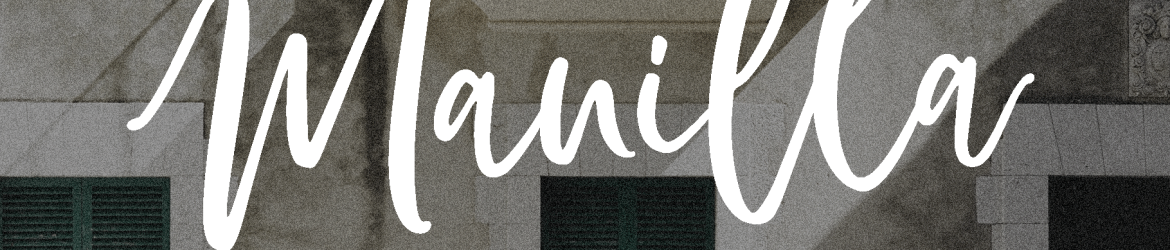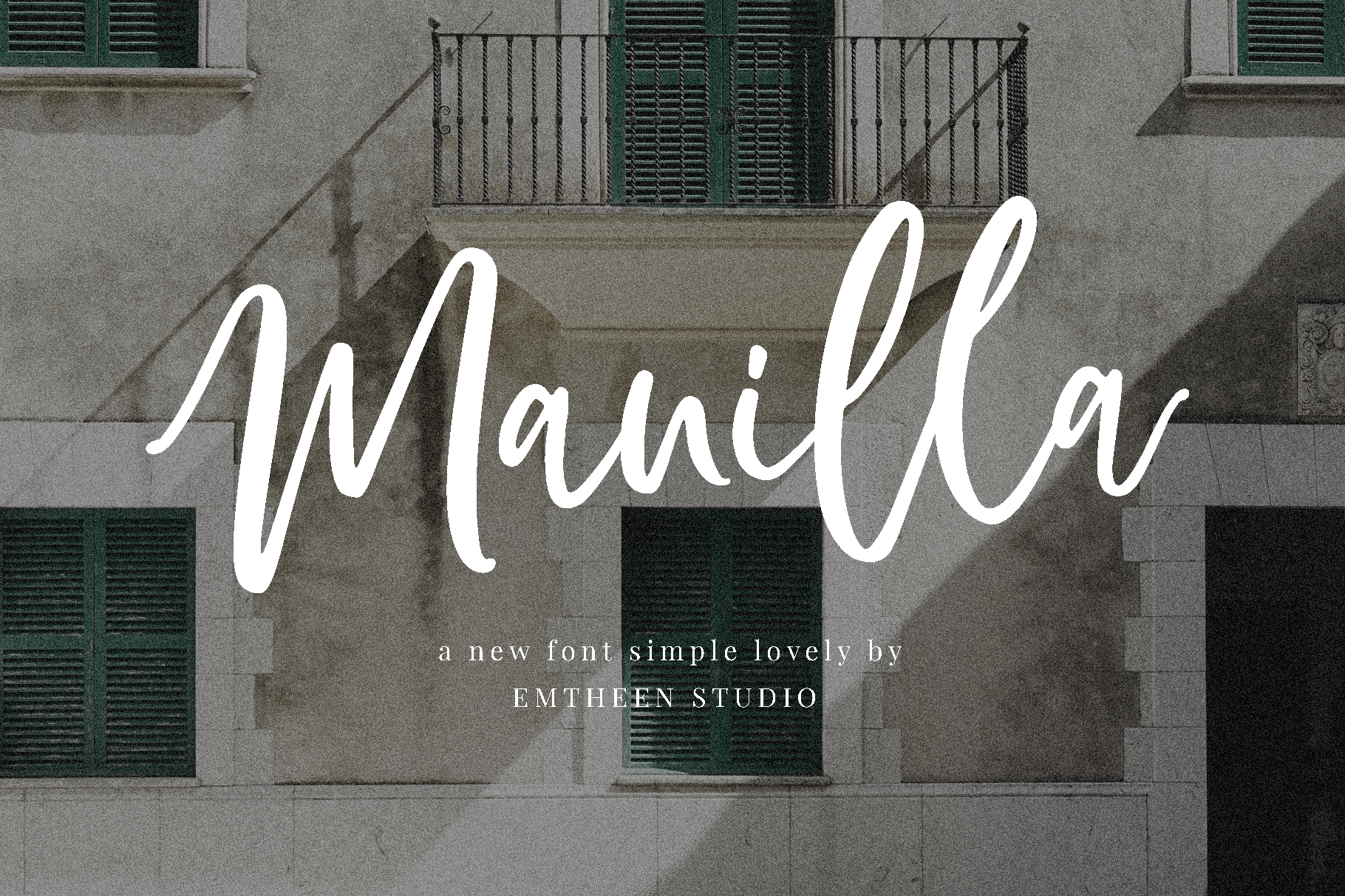
Manilla Script Font – Fonte Grátis
Manilla Script Font
A Manilla Script Font é uma nova opção no catálogo de 1001fonts, desenvolvida para quem busca uma fonte simples e encantadora que possa dar um toque especial a qualquer projeto. Essa fonte é perfeita tanto para títulos quanto para o cotidiano das palavras, apresentando características como letras maiúsculas, minúsculas, números e pontuação em todos os idiomas multilinguês. Além disso, inclui ligaturas e alternativas de caracteres que tornam a experiência de uso ainda mais intuitiva. A Manilla Script é uma fonte script simples e versátil, projetada para se adaptar a diversos ambientes, seja um blog, uma etiqueta ou até mesmo um convite de casamento. Com suporte para extensões .ttf e .otf, ela oferece flexibilidade para uso em qualquer plataforma. Seja você criando um design de blog com um visual elegante, projetando um anúncio para a sua marca, criando uma capa de capa fashion, ou mesmo montando cartões de boas-vindas personalizados, a Manilla Script Font é perfeita para qualquer projeto. Ela atende ao seu propósito de tornar seus trabalhos ainda mais profissionais e atraentes.